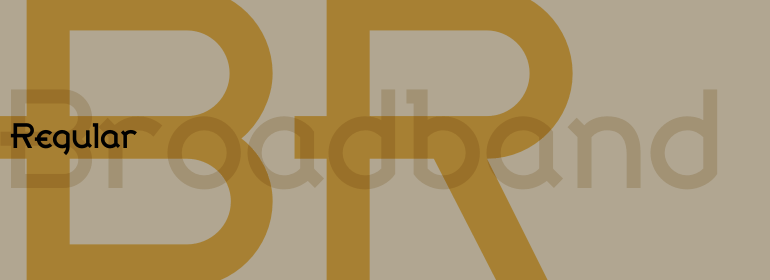
Broadband™
Broadband™,这款字体结构工整、笔画清晰,兼顾美观与易读性,适用于标题、正文、海报、包装、LOGO 等多种场景。字形优雅稳定,风格百搭耐看,适配日常排版与创意设计,让文字呈现更舒适、更具质感。Broadband™一笔一画,皆是细节,以均衡的比例、流畅的线条打造舒适视觉体验,字形端正大气,风格简约现代。无论是商业设计、品牌宣传还是日常排版,都能轻松驾驭,让文字更有格调与力量。Broadband™字体下载。